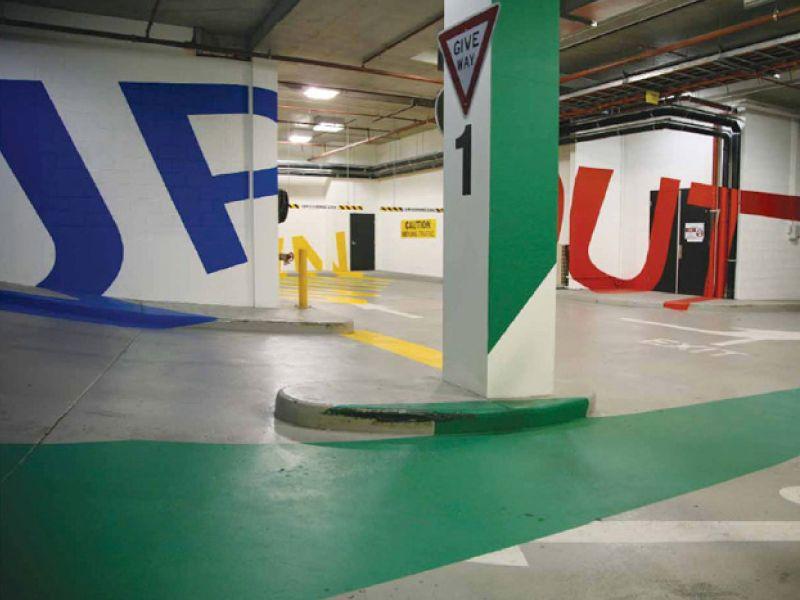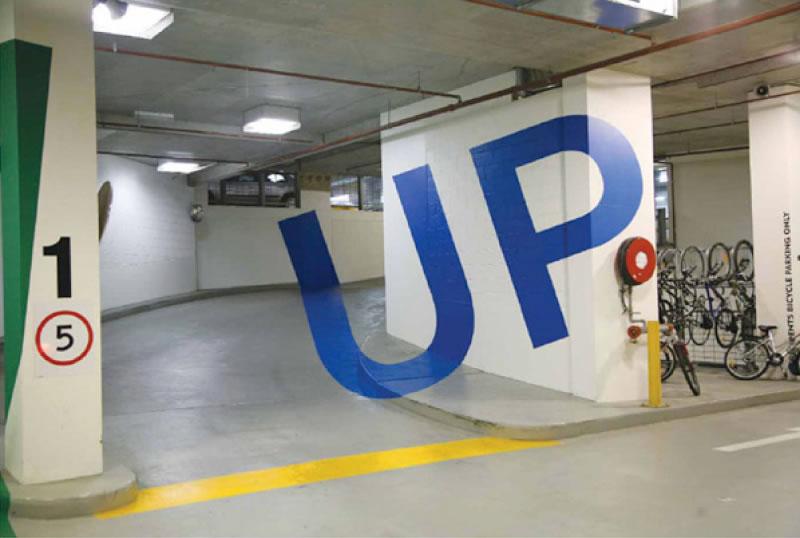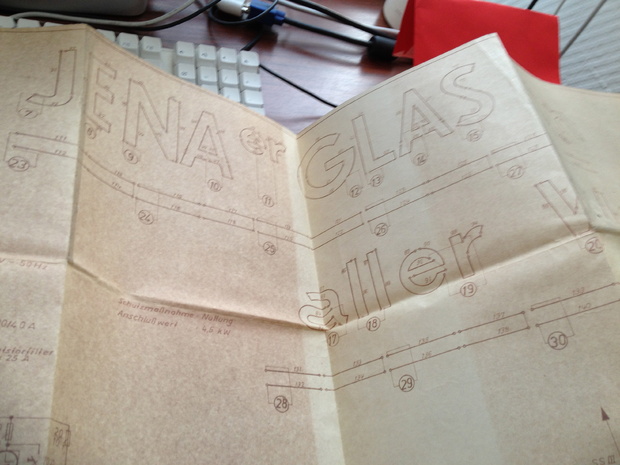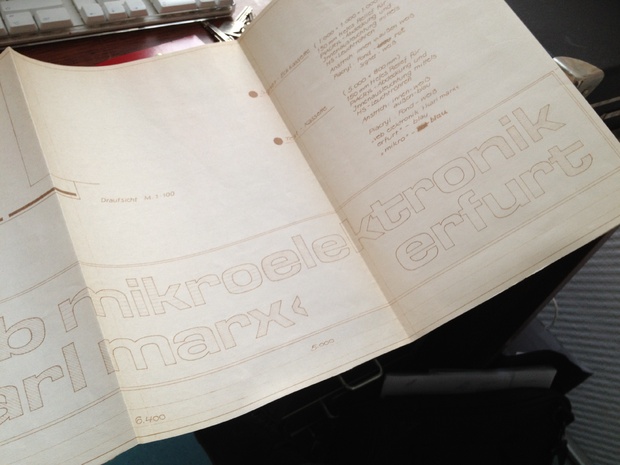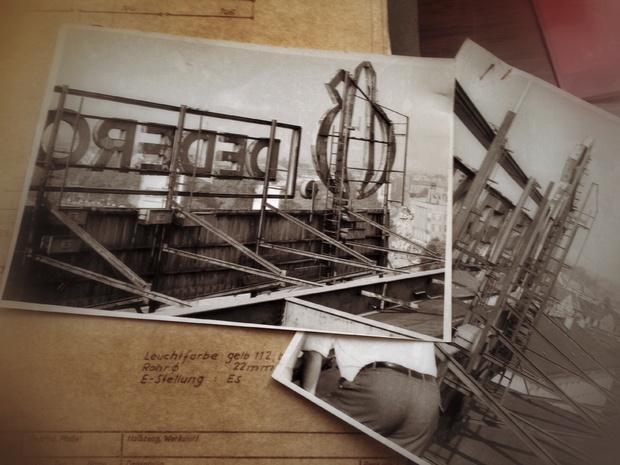
Wurde grundsätzlich schon tausend Mal gesehen, ist aber manchmal nicht allein Kunst, sondern erfüllt sogar eine Funktion:
Die Funktion ist hier aber eher »Kunst«. Im Sinne der Benutzbarkeit wäre jede unverzerrte Darstellung besser. Wer den Ausgang sucht, will nicht erst den einen Punkt finden, von wo aus er »Ausgang« lesen kann.
Luz Nas Vielas(Light in the Alleys) is a beautiful and inspiring participative Urban Art project created by Spain based collaborative Boa Mistura in the heart and streets of São Paulo’s favelas.
Ich korrigiere: … das urban-brasilianische Ambiente mit der frohen Farbigkeit steigern ja noch das Seherlebnis. :-)
Kunst ohne Funktion ist auch schön …
Es gab ja hier im Forum schon einige Diskussion, ob die Ausstellungsstücke des Berliner Buchstabenmuseums überhaupt bewahrenswert seien. Der meiner Meinung nach größte Schatz des Museum ist aber eine neue Übernahme ganz ohne physische Buchstaben: die kompletten Akten und Pläne eines großen DDR-Betriebes, der Neon-Beschriftungen fertigte. Die Akten enthalten die kompletten Planungen, Berechnungen und natürlich Ansichten der Beschilderungen, die in verschiedensten ostdeutschen Städten zu sehen waren. Teilweise sind detaillierte Handzeichnungen ganzer Häuserfronten darin. Ich war zumindest hin und weg und freue mich schon darauf, wenn dieser Schatz irgendwann einmal aufgearbeitet und öffentlich präsentiert werden wird.
urban lettering
dort alle eindrücke aus urlaubsreisen und dergleichen die irgendwas mit typografie
im öffentlichen raum zu tun haben.
ralf, falls das nicht in deiunem sinne ist, zwecks speicherplatz — kurze pm reicht und ich lagere die bilder aus.
Buch samt Typo als Leckerbissen – Schmecken lassen! :-)
Das echte und einzige Kochbuch, das man tatsächlich lesen, kochen und verzehren kann.
Zu 100 % aus frischem Nudelteig lässt es sich aufklappen, füllen, bestreuen und schließlich kochen. Verpackt als klassische Lasagne. Entwickelt wurde es als ein Sonderprojekt für einen großen Verlag.
Vielleicht weil das s so "herzig" ist? :-)